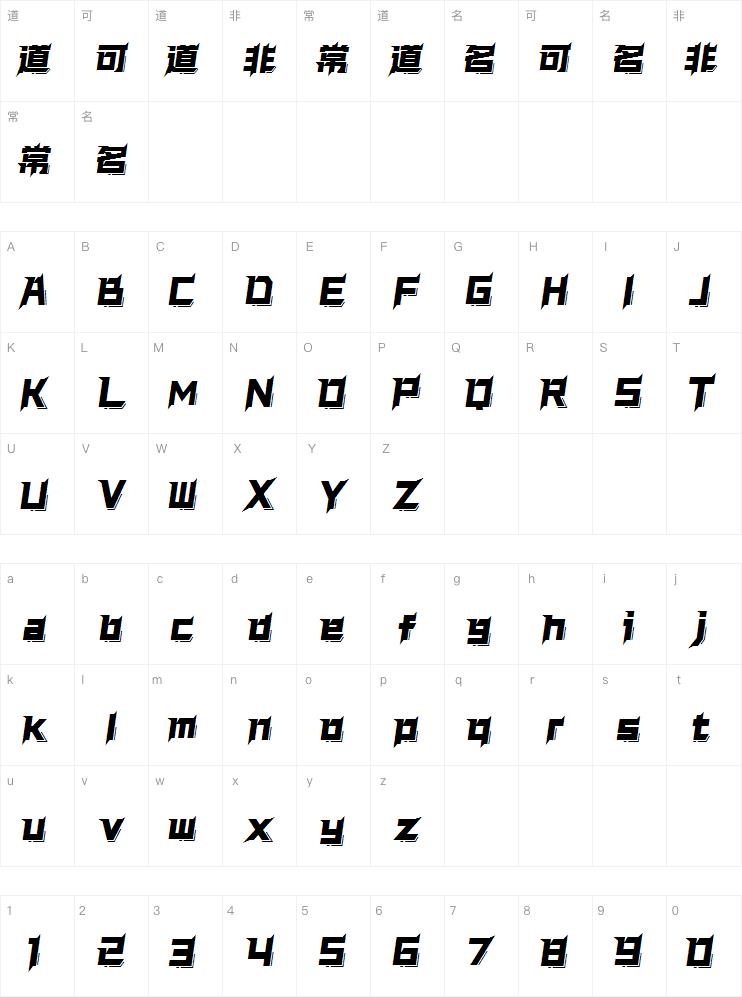
潮笑社巨浪简 特粗是一款充满科技感的创意黑体,整体向右倾斜设计,中宫饱满宽博,笔画粗壮硬朗,并在笔画切口与转折处设计大量错落的尖角装饰与斜切设计,极大增强了视觉张力。字体的右下方笔画带有特殊的虚实描线,如同水下高速冲刺的武器周边带起的气泡,带给人速度与科技感。能够适用于游戏宣传、包装印刷、商业海报与品牌宣传等领域。